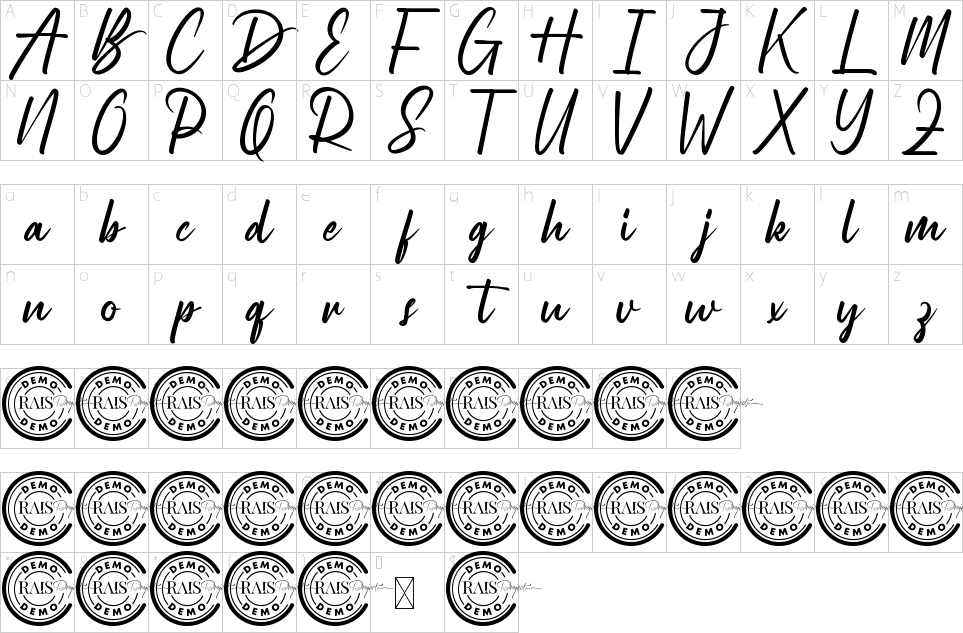
Descubra a beleza da fonte ‘Perfect Bright’ no seu próximo projeto. Esta fonte foi projetada por raisproject e é uma escolha ótima para designers e criativos que buscam uma aparência clara e alegre. ‘Perfect Bright’ se destaca por sua simplicidade e clareza, o que a torna uma opção versátil para diferentes estilos de design. Com uma popularidade de 5,300 downloads, ‘Perfect Bright’ é uma fonte de alta qualidade que valoriza tanto designers profissionais quanto aqueles iniciantes. Experimente-a e descubra por si mesmo o poder desta fonte. Descarregue ‘Perfect Bright’ para seu computador Windows e Mac e adicione a personalidade a cada projeto.